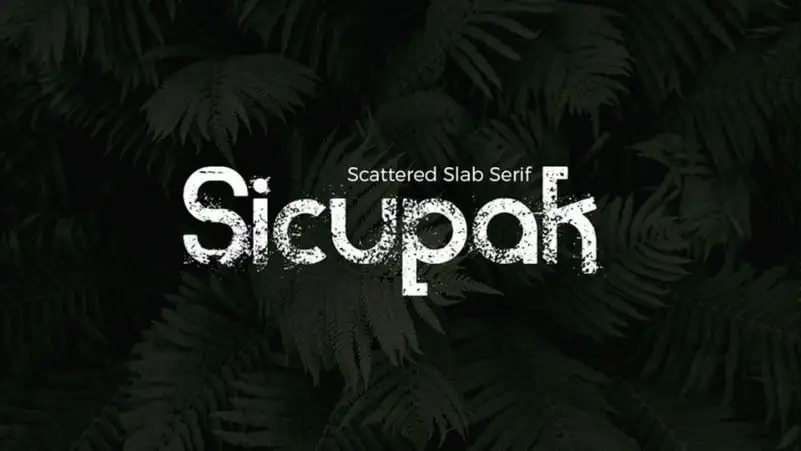
Sicupak Display Font
A Sicupak Display Font é uma escolha perfeita para aqueles que procuram um ar rusticado e vintage em seus projetos digitais. Ela foi criada especialmente para designers que desejam um toque clássico e alegre nos seus trabalhos, seja para headlines, posteres ou qualquer outro tipo de arte digital. Manufacturada pela Jarnawi Saja, Sicupak é uma fonte slab serif que vai bem em projetos grunge, onde sua dispersão despojada cai perfeitamente na harmonia do estilo vintage moderno. Com uma ampla gama de letras maiúsculas e minúsculas, números e símbolos completos, a Sicupak Display é um elemento versátil que se encaixa em qualquer projeto. Ela não apenas destaca-se nas criações grunge com seu design despojado e moderno, mas também brilha em headlines e posteres que exigem um toque elegante e clássico. Seja para uma campanha de marketing digital ou uma publicação de arte independente, a Sicupak Display é uma escolha inteligente para manter seu design único e autêntico, sem comprometer sua legibilidade.